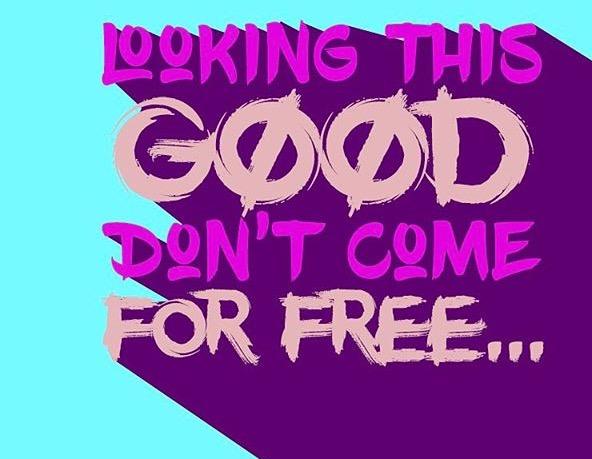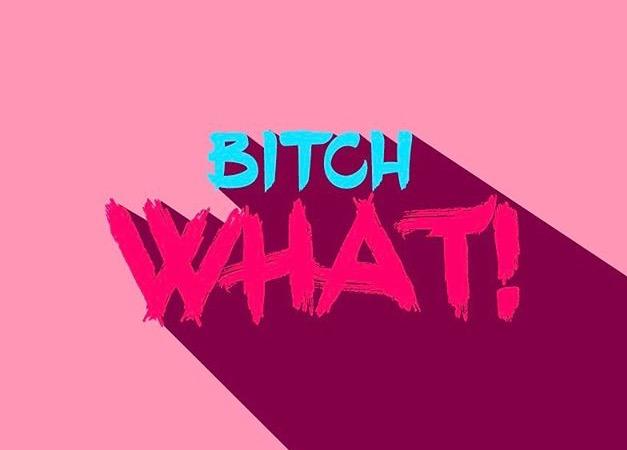
Welcher Font ist das? (Cha-Ching)
kennt jemand diese Schriftart, oder eine Möglichkeit wie man Bilder mit solchen Texten schreiben kann? Gibt es dafür irgendeine App für Iphone?
Cha-Ching ist aus der BlowBrush, free for personal use.
Und diese Schatteneffekte sind dann sehr wahrscheinlich von Hand mit einer Grafiksoftware gemacht. Sie fangen ja nicht bei jeder Zacke der Buchstaben an.